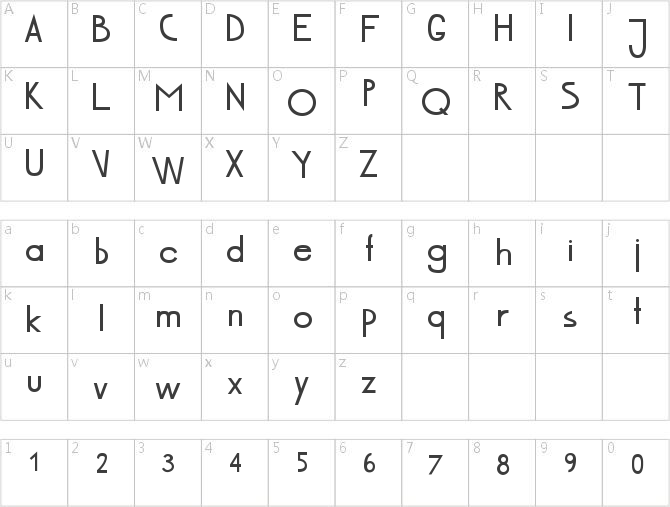
字体名称: Bus_211
Bus_211_Portugal_Muenchen_Bold
Bus_211_Portugal_Muenchen_Bold字体字库是一款让人赏心悦目、百看不厌的英文字体,适合各类广告和产品包装设计应用,字体大小0.05MB,格式为ttf字体,上传用户是Me / ,yD ,作者/版权方为未知